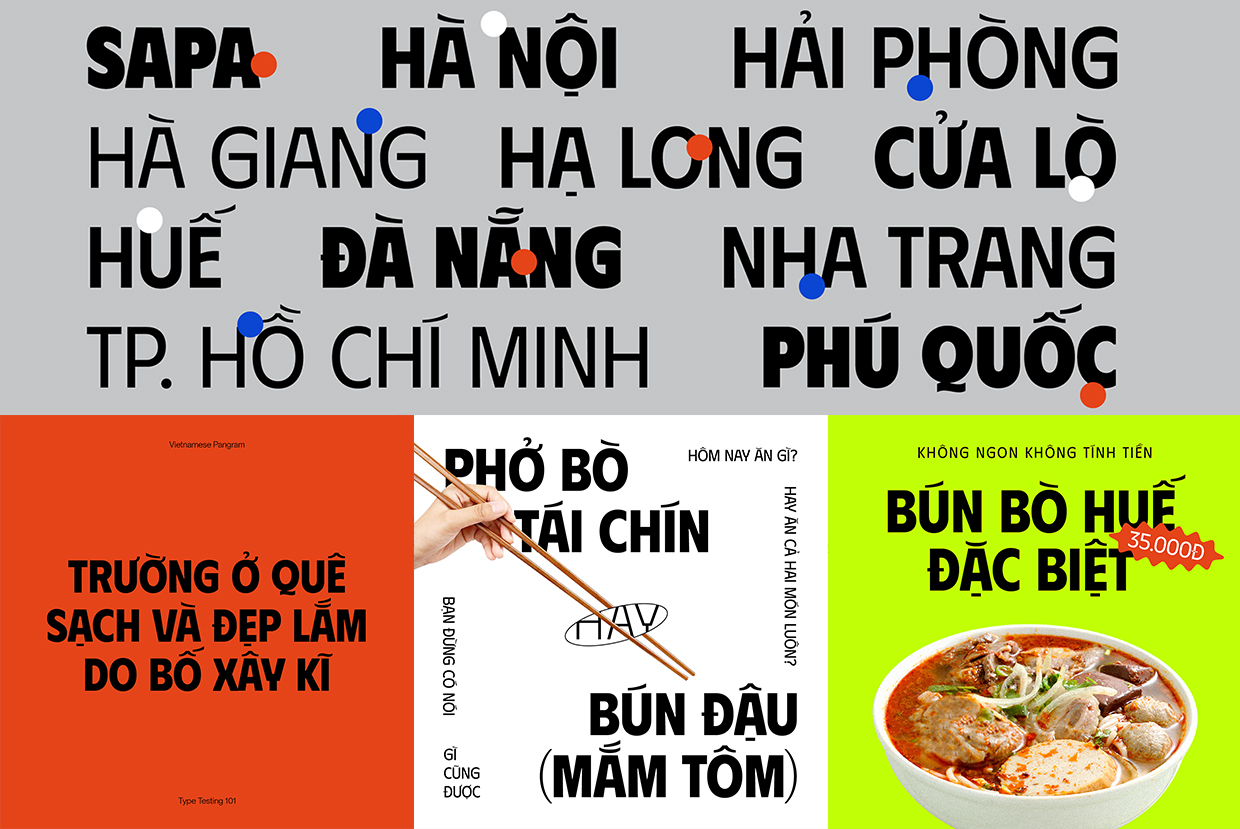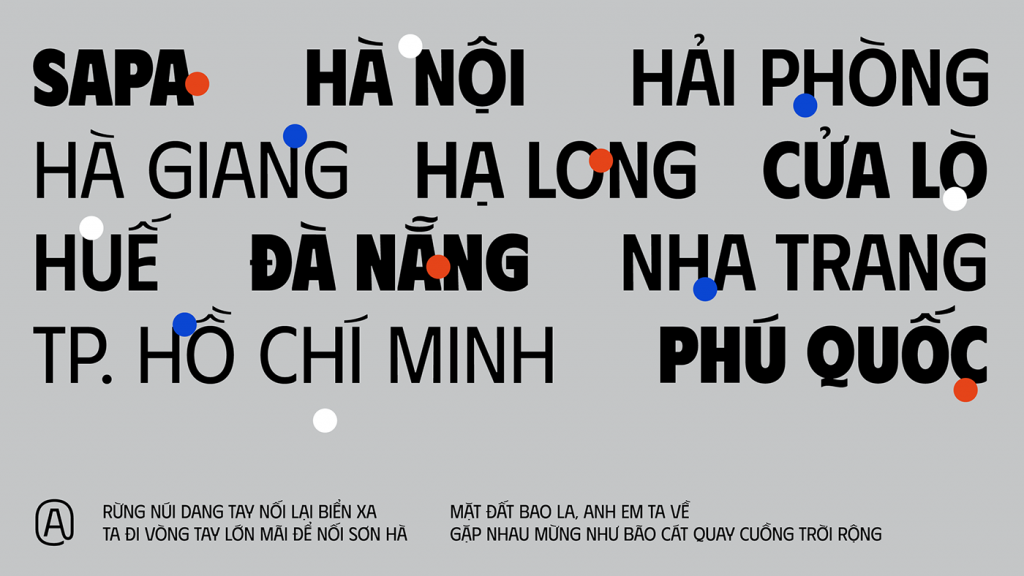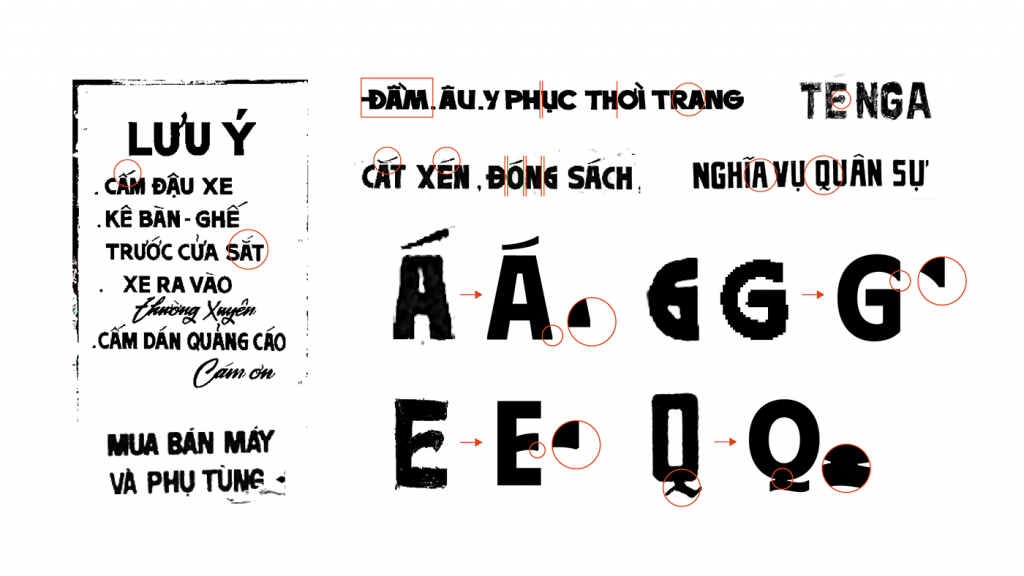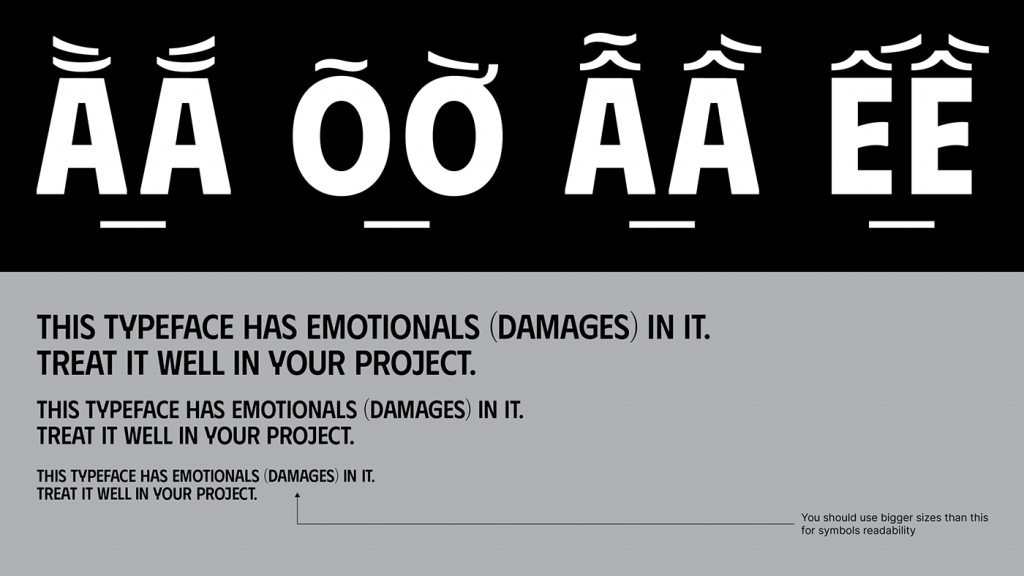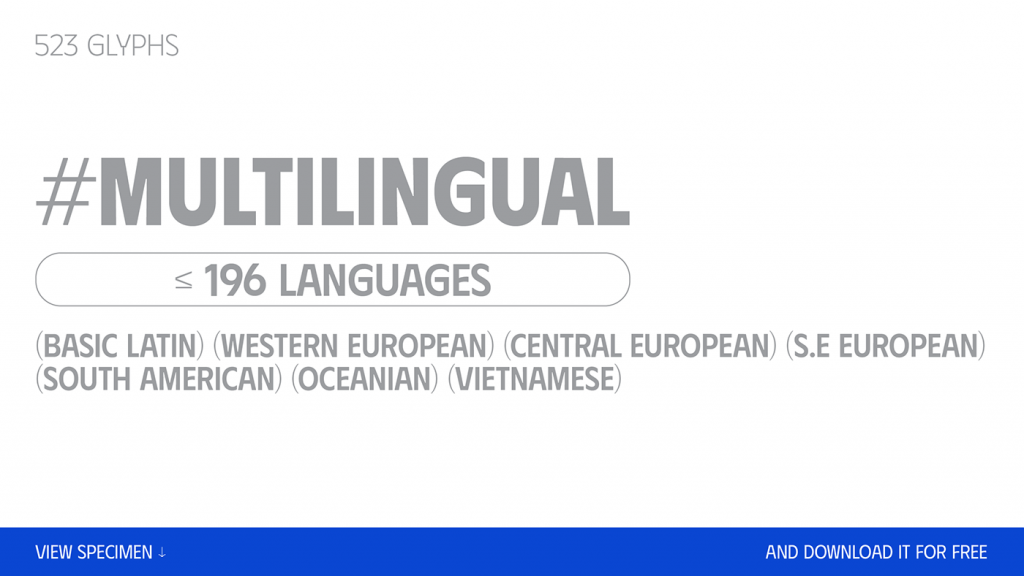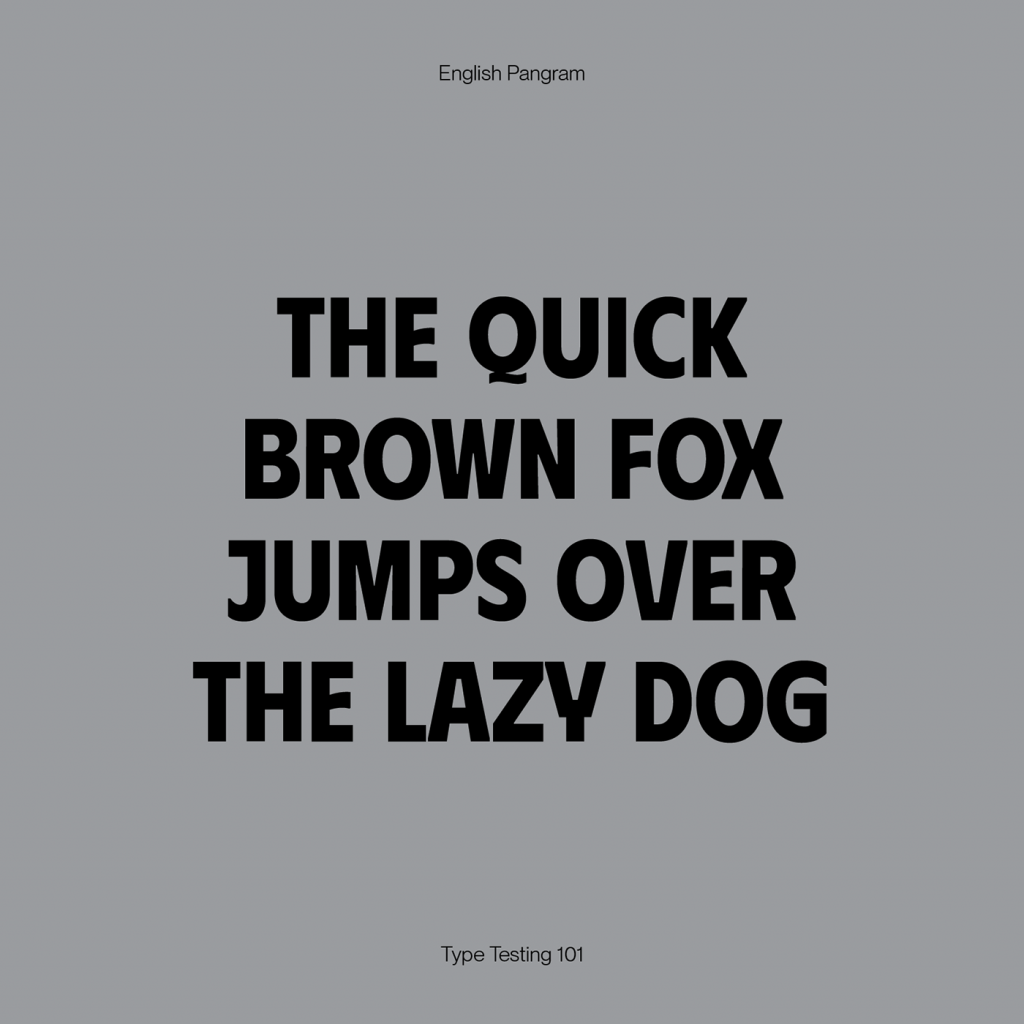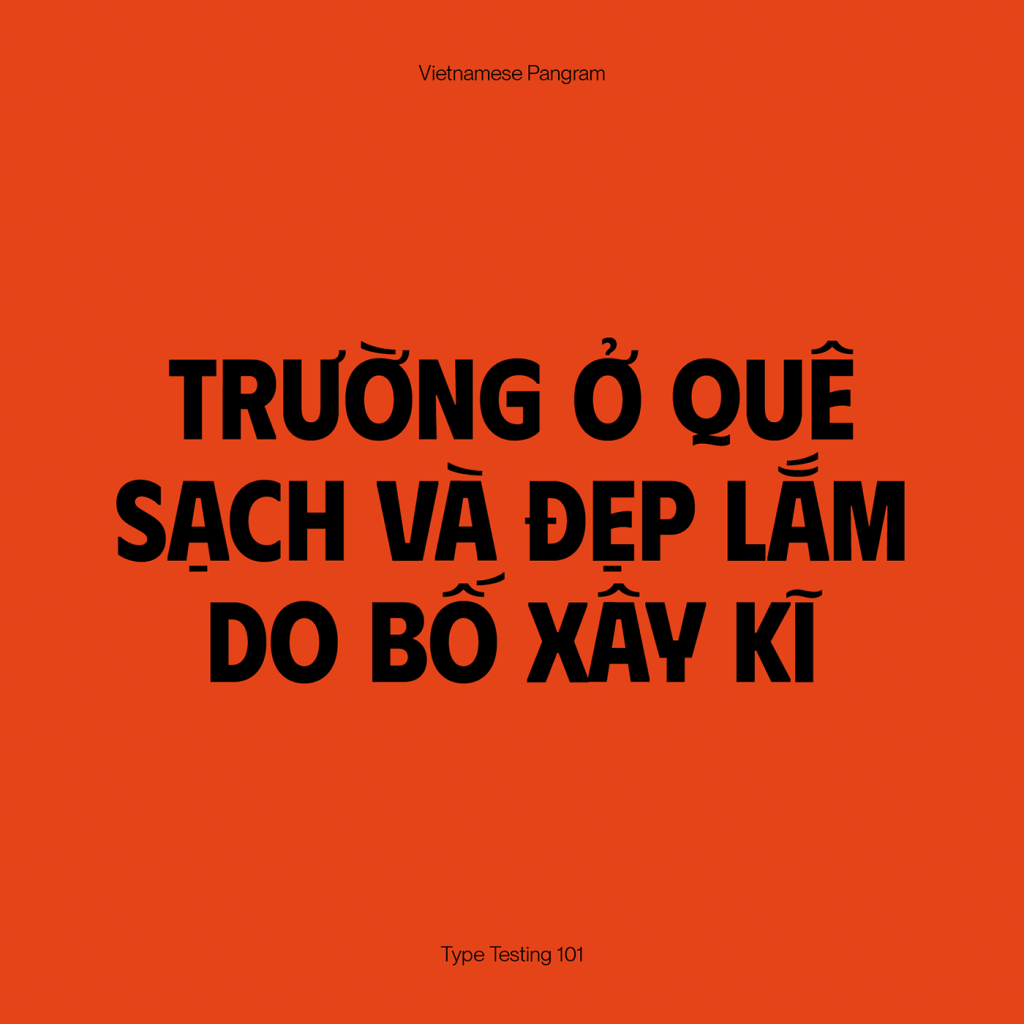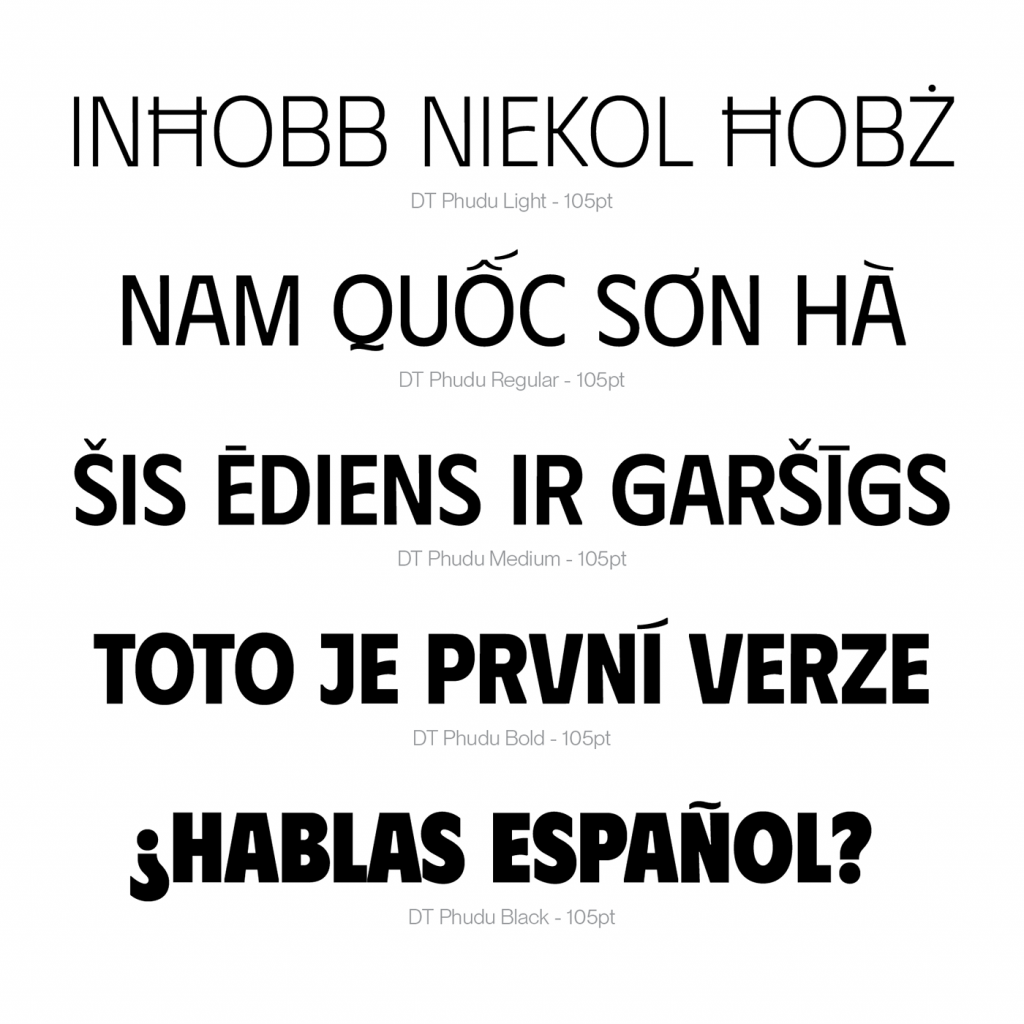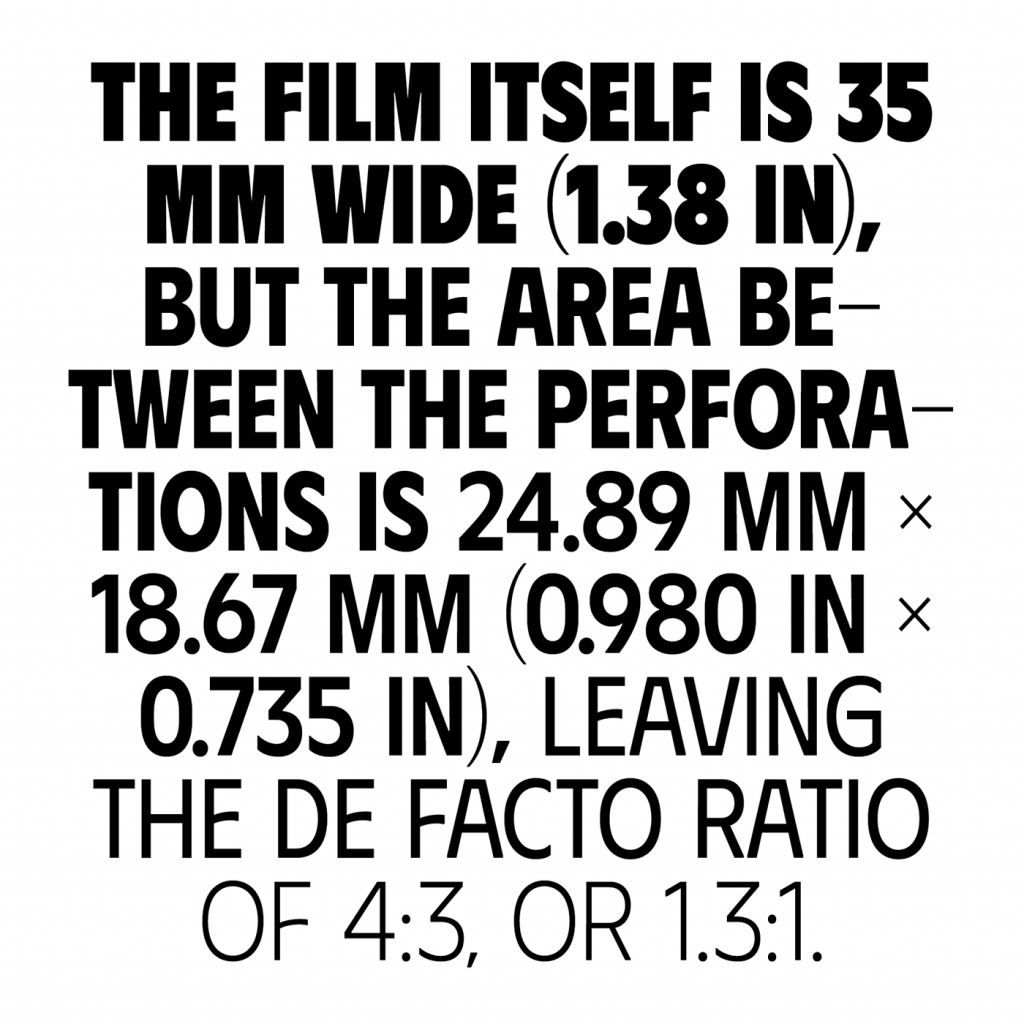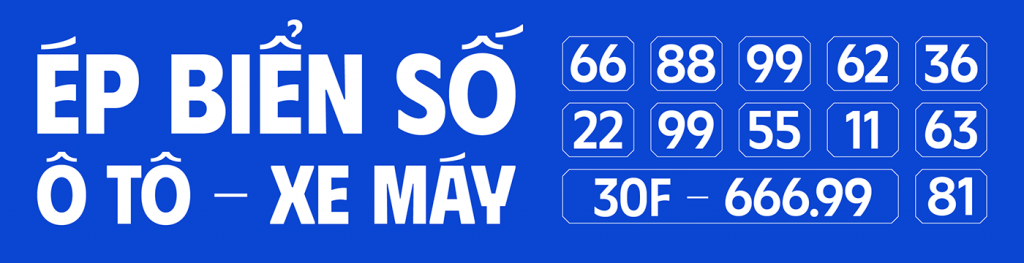
Tác giả Dương Trần vừa giới thiệu một bộ display sans-serif (5 định lượng) hỗ trợ đầy đủ Tiếng Việt và khoảng 195 ngôn ngữ khác, dựa theo tiêu chí dễ dùng, dễ tiếp cận và dễ có tính “Việt”.
Tác giả chia sẻ: “mặc dù là cảm hứng từ các chữ cái xuất hiện trên biển bảng, nhưng mình không chỉ phục dựng chúng mà cải tiến chút để hợp thời đại hơn. Bộ này được ra mắt bởi mình thấy lượng font biển bảng tự làm bởi người Việt vẫn còn ít, và cũng coi như có thêm 1 lựa chọn cho mọi người mỗi khi nghĩ chọn font gì cho các dự án. Ngoài ra, định lượng càng mỏng thì khoảng cách với kích thước càng tăng chút để font dễ đọc hơn.”